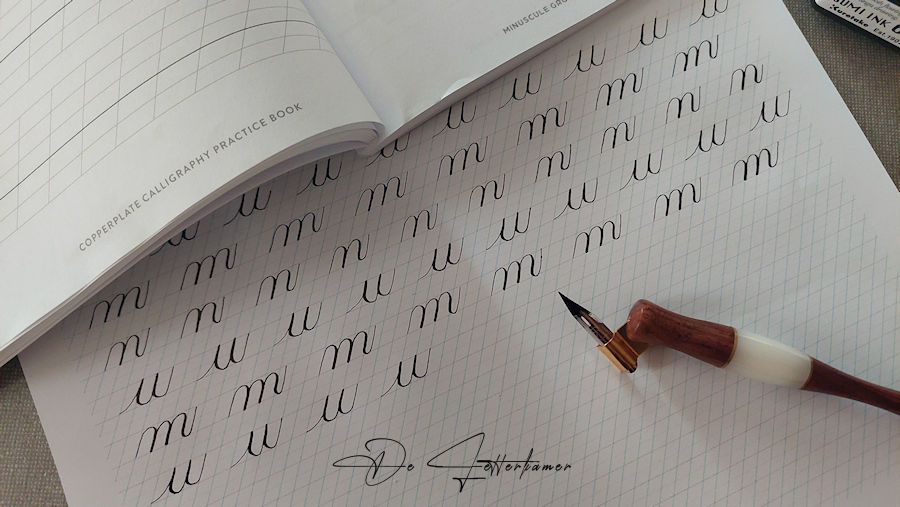
Even een pauze genomen, dit mag ook eens, kalligrafie is een afwisseling van mijn andere hobby, zo even tussendoor, het hoeft niet lang te duren. En eigenlijk ben je daar heel vlug mee weg.
De avond valt vlugger, je voelt dat september er aan komt, het wordt weer onrustiger, meer auto’s, fietsers, meer verkeer. Het gejaagd leven is er weer. Tijd om even stil te staan. Mijn oefenboek genomen, en mijn printpapier terug, mijn voorkeur gaat naar dit, zowel het papier als de guidelines. Het is toch wel even zoeken wat vind ik nu comfortabel.
Ik heb gezien in het boek (boek: Copperplate Calligraphy Practice Book), dat er verschillende groepen zijn. Groep 1, de kleine letters: overturns and underturns daar zitten de letters i, t, u, m en n in.
Zo, tot zover zit ik. Deze avond ging het heel goed. Tot mijn uur is bereikt, dan begin ik te missen. Dan moet ik stoppen.
Mijn dochter heeft dit ook nog gedaan en was blij verrast met het resultaat. Ze gaat me wat dicteren, zei ze. Ben eens benieuwd!
Ik denk zo een 2 keer per week oefenen is voldoende voor mij, het was nog even zoeken hoeveel per week, 2 uurtjes per week lijkt me voldoende.